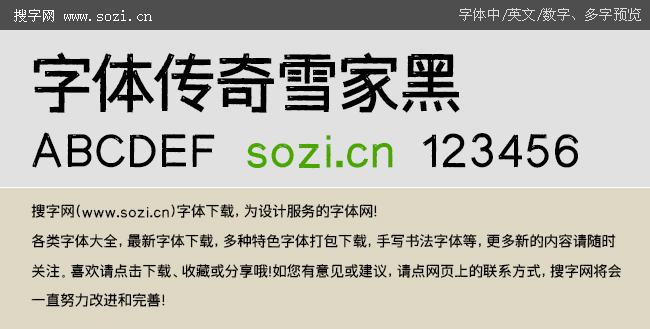
字體傳奇雪家黑
搜字網(wǎng)給大家提供一款字體傳奇雪家黑中文字體下載,字體傳奇雪家黑由張家佳字庫團(tuán)成員郭小雪設(shè)計(jì),字庫命名由他的名字和家鄉(xiāng)張家口組合,取名雪家黑,這款字體結(jié)構(gòu)根據(jù)黑體進(jìn)行設(shè)計(jì),筆畫復(fù)古元素裝飾應(yīng)用。免費(fèi)供大家使用。適合應(yīng)用于藝術(shù)設(shè)計(jì)、平面宣傳設(shè)計(jì)、網(wǎng)頁設(shè)計(jì)、海報(bào)設(shè)計(jì)等應(yīng)用。